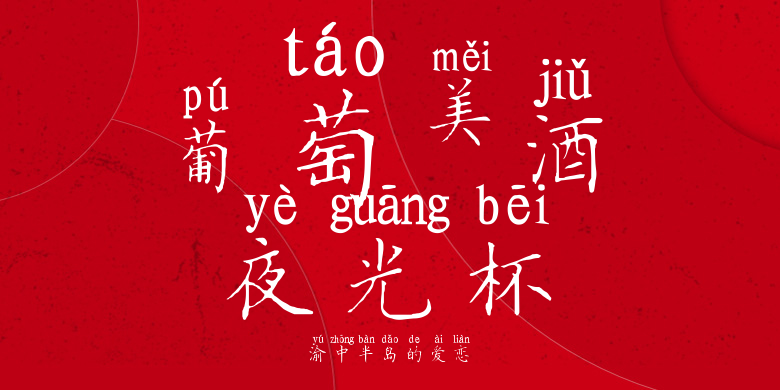
渝中半岛的爱恋
渝中半岛的爱恋,这款字体结构工整、笔画清晰,兼顾美观与易读性,适用于标题、正文、海报、包装、LOGO 等多种场景。字形优雅稳定,风格百搭耐看,适配日常排版与创意设计,让文字呈现更舒适、更具质感。渝中半岛的爱恋一笔一画,皆是细节,以均衡的比例、流畅的线条打造舒适视觉体验,字形端正大气,风格简约现代。无论是商业设计、品牌宣传还是日常排版,都能轻松驾驭,让文字更有格调与力量。渝中半岛的爱恋字体下载。